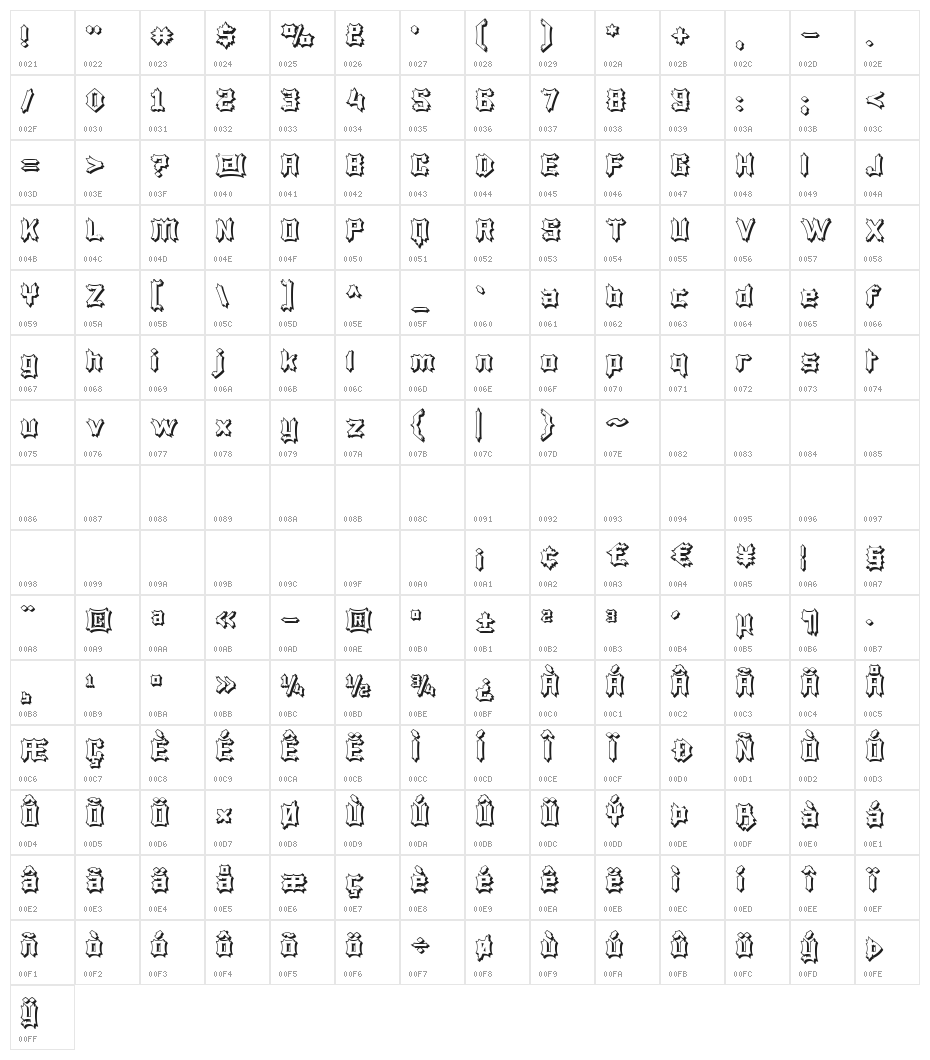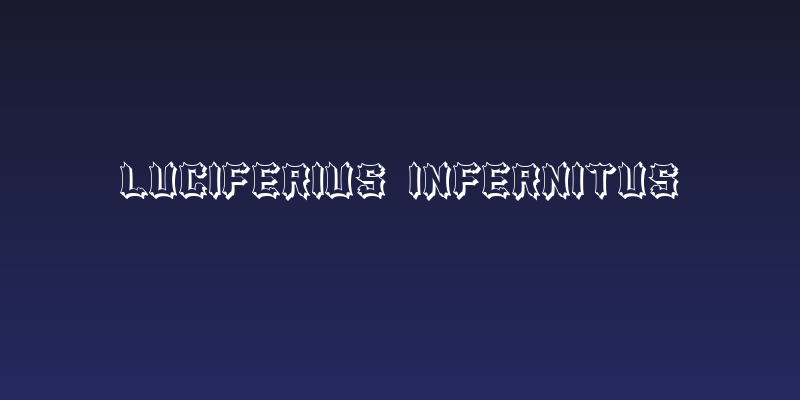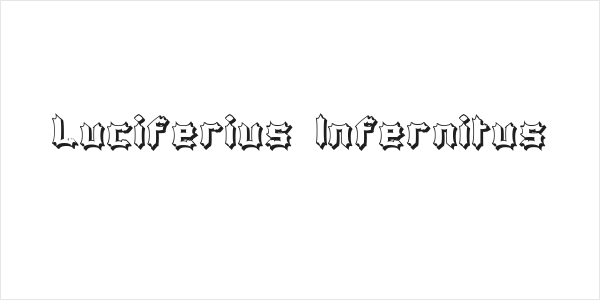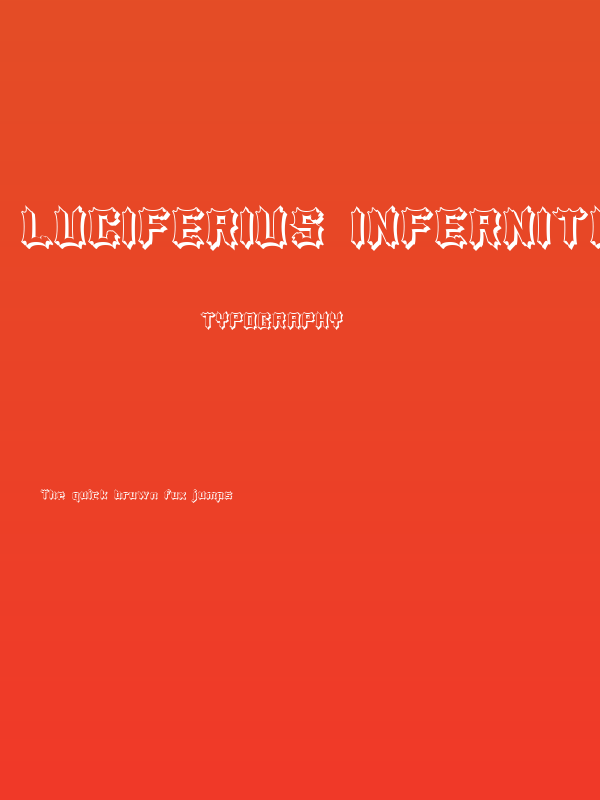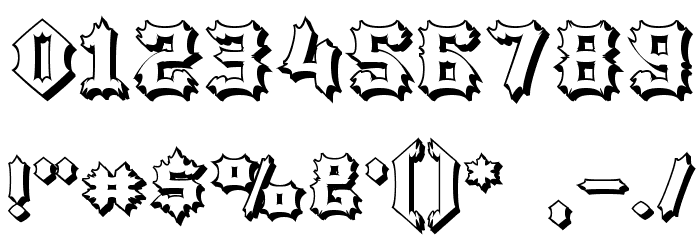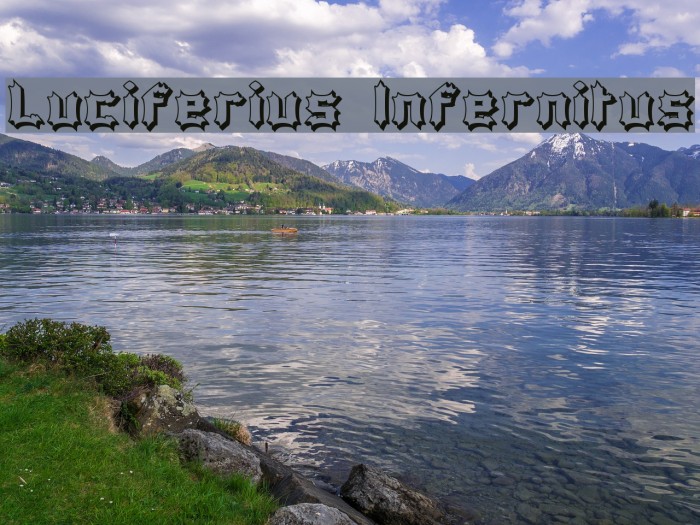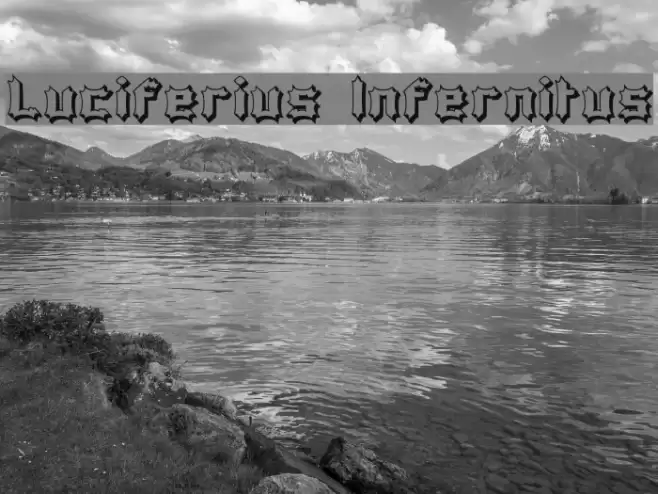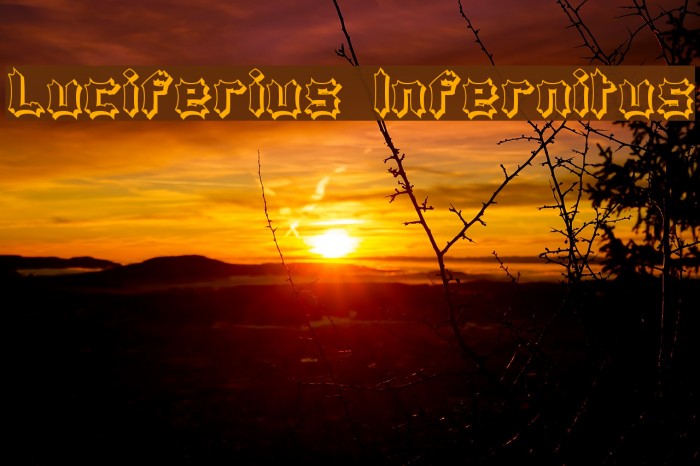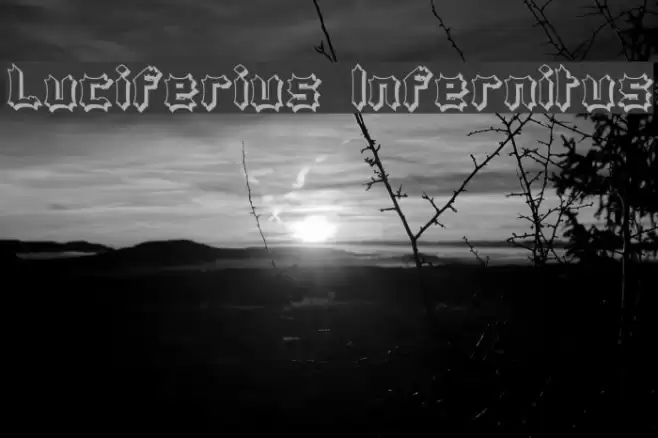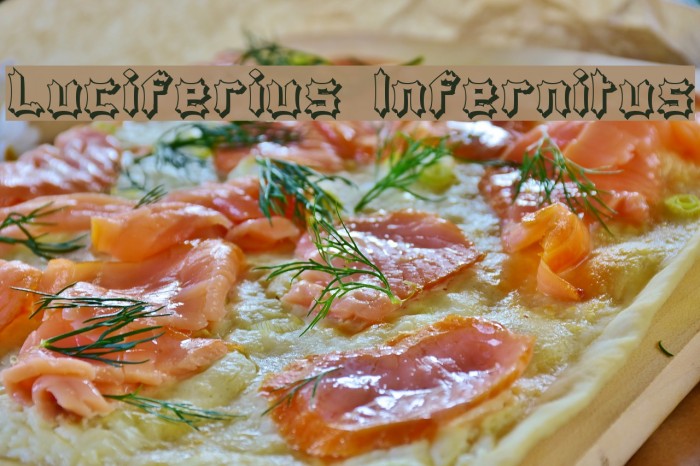
Luciferius Infernitus Font
✎ Outline
Fonts by Apostrophic Lab
| Categorii | Outline |
| Stil general | Gothic, Decorative |
| Proiecte propuse | Ideal for horror-themed designs, album covers, posters, video game graphics, and branding for edgy or alternative products. |